输入名字,挑一个样式,下载 PNG。就这么简单,大约十秒钟。
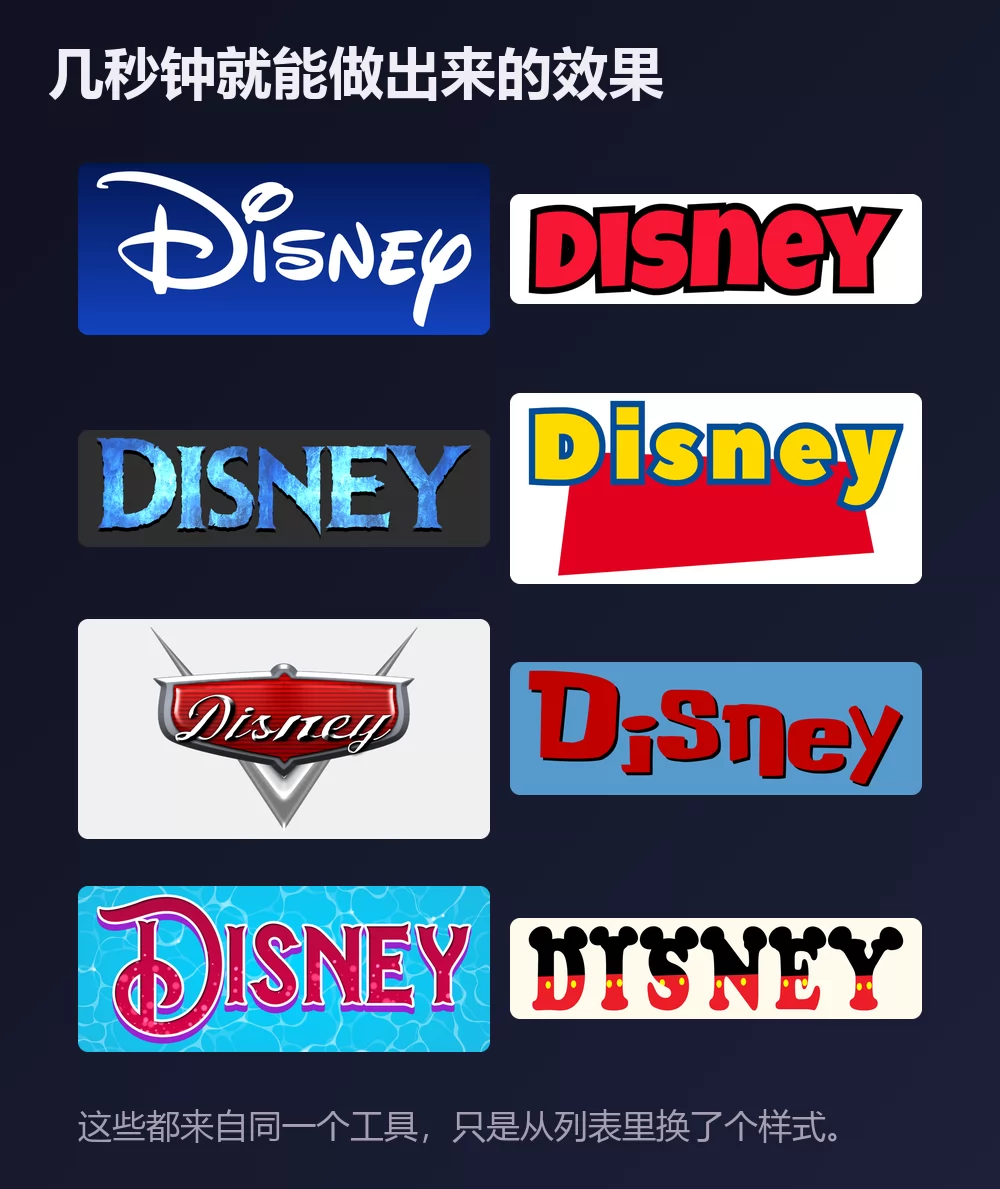
这些都来自同一个迪士尼字体生成器,只是从列表里换了个样式。无需安装,无需账号。
关于迪士尼字体
华特迪士尼公司由华特·迪士尼和罗伊·O·迪士尼兄弟于 1923 年创立,如今已是全球最大的媒体公司之一。米奇是它最知名的角色,也是官方吉祥物。
标志上的字样是华特·迪士尼签名的风格化版本。它从 1956 年起就是公司标志,却从未作为字体发布:没有任何官方文件可供安装。大家转而下载的是 Waltograph,由 Justin Callaghan 按照标志字样绘制。它有两个版本:Waltograph 42,含大小写字母,外加少量连字和替代字形;Waltograph UI,一种单一大小写的版本,为的是在小字号和屏幕上依然清晰。两者都可免费用于个人用途。
怎样做迪士尼文字
第一步:输入名字
打开生成器,把示例文字换成你自己的:孩子的名字、派对的标题、旅行 T 恤上的姓氏。字母会随着输入实时重绘。请保持首字母大写、其余小写:签名风格是手写体,全部大写会丢掉那个高高绕圈的 D,而它正是让人一眼认出迪士尼的关键。
第二步:挑一个样式
经典款是宝蓝色渐变上的白色签名体。在"样式"选项卡里,填充、描边和阴影可以分别调整,所以你可以保留字形,把颜色换到别处:婚礼用深蓝配金色,公主派对用粉色。
第三步:选好尺寸
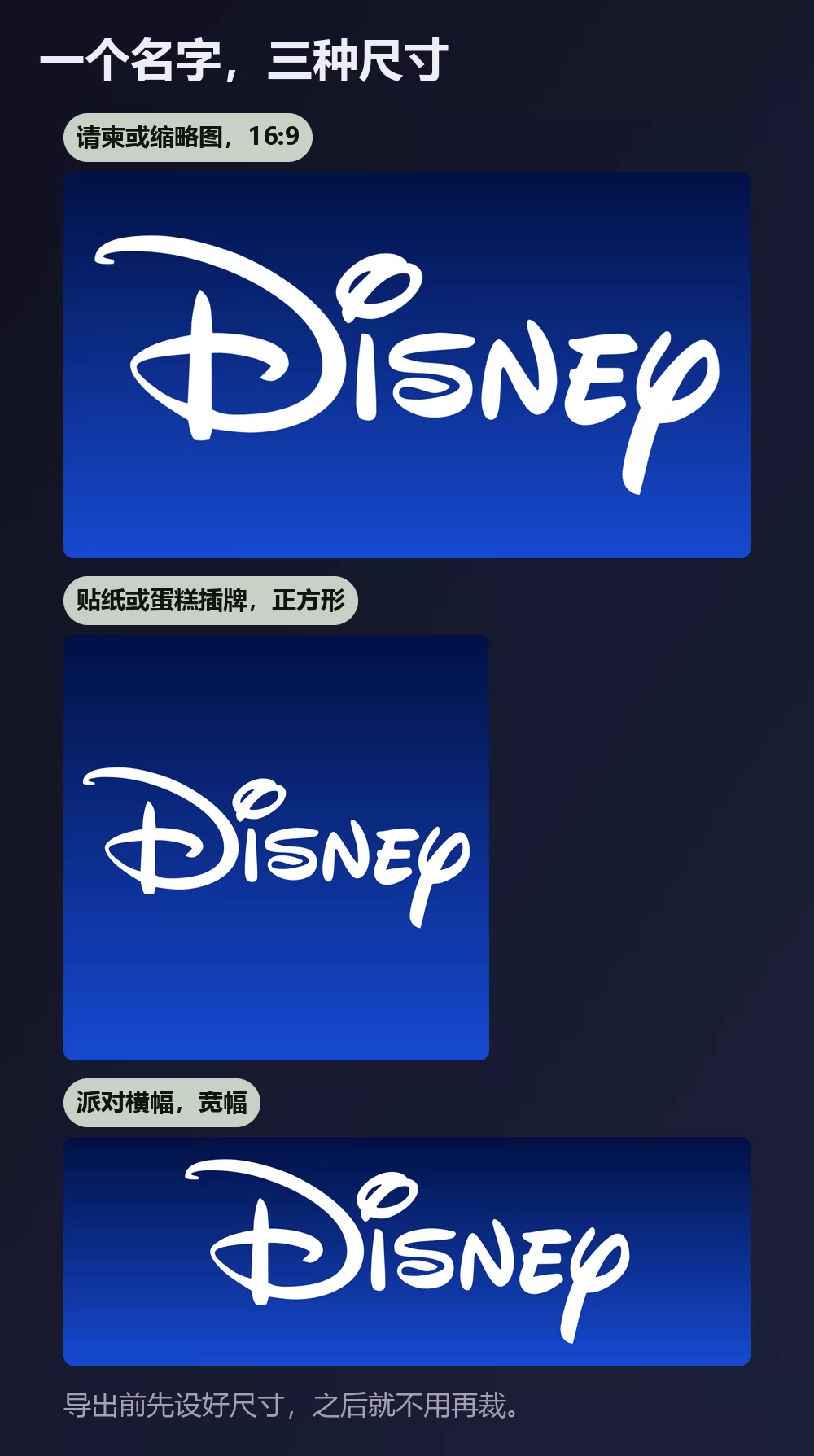
导出前先设好尺寸,之后就不用再裁。请柬或视频缩略图用 16:9,贴纸或蛋糕插牌用正方形,挂在墙上的横幅用宽条。
第四步:下载
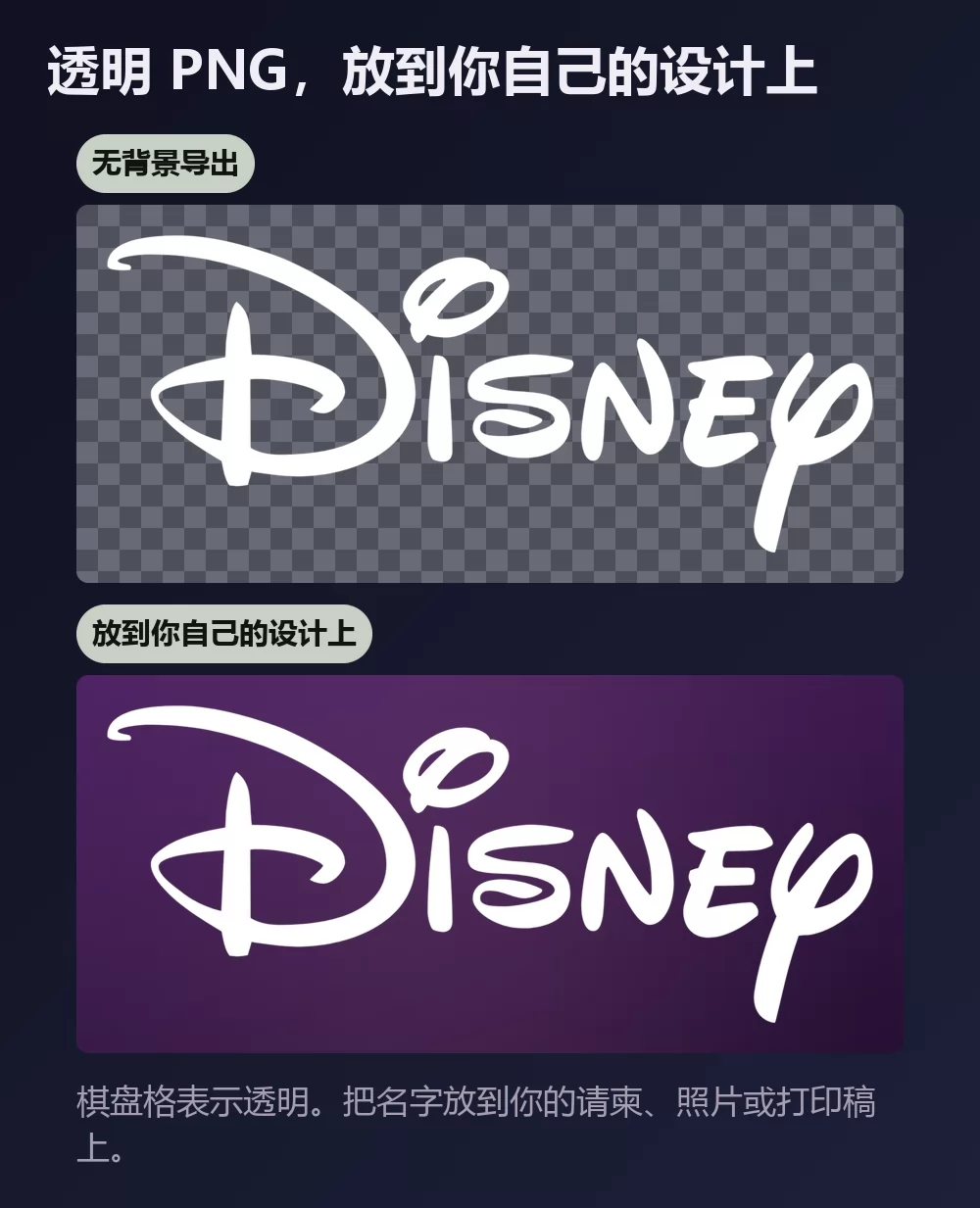
如果打算把名字放到自己的设计上,就在"下载"选项卡里选透明 PNG。这是大多数人错过的选项,而对派对打印品来说恰恰是最要紧的:你自己的背景,名字在上面,周围没有蓝色方框。
名字一长,宽度很快就满了
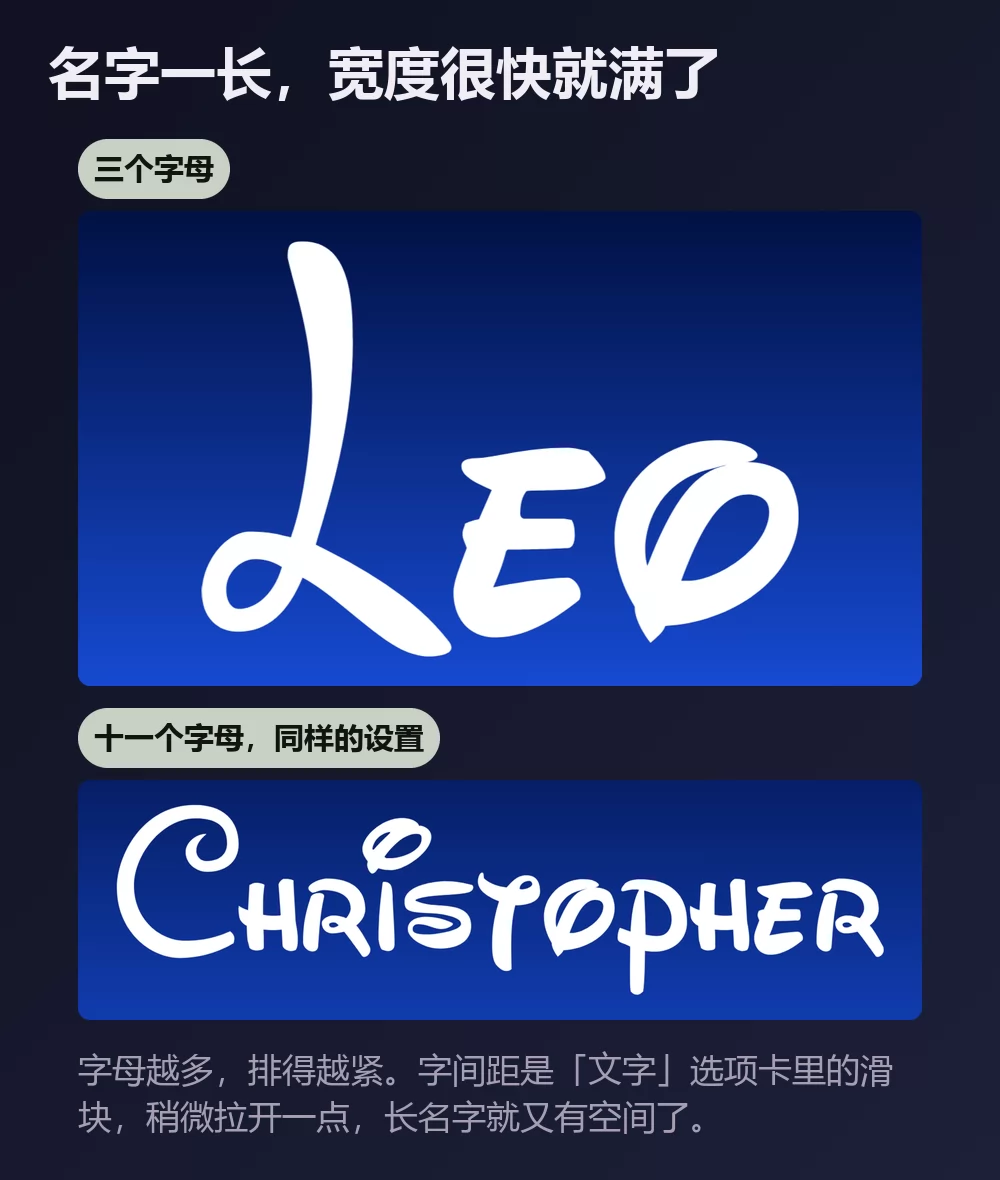
字母越多,排得越紧。字间距是"文字"选项卡里的滑块:稍微拉开一点,长名字就不再显得局促。同一个选项卡里还有缩放、行高、弧度和旋转。
签名风格,还是米奇风格
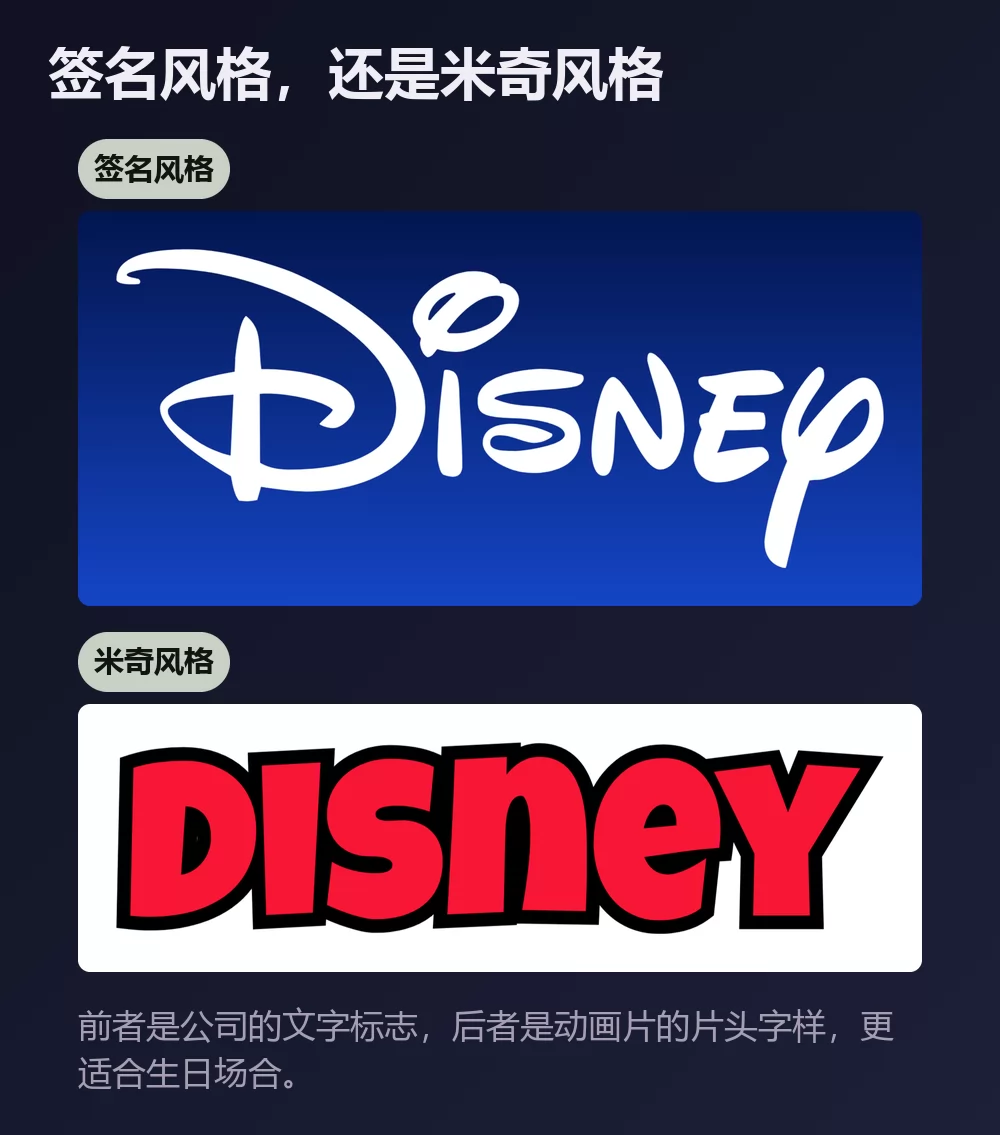
签名风格是公司的文字标志:流畅的手写体,带高高绕圈的 D,蓝底白字。大多数人说"迪士尼字体"时,脑子里想的就是它。
米奇风格是动画片的片头字样:带黑色描边的粗壮红色大写字母,米奇短片里用的那种。它不带任何公司标识,隔着房间也看得清,办周岁生日的话通常比签名体更合适。米奇字体生成器里有现成的预设。
想安装字体的话,选哪一款
标志本身不是字体。它是定制的手绘字样,所以任何叫"迪士尼字体"的文件,都是别人对它的再现。
Waltograph,Justin Callaghan 所作,是大家都在用的那款再现。它在 DaFont 上已有大约二十年,下载量超过一千三百万次。下载包里有两个文件,waltograph42.otf 和 waltographUI.ttf,标注为个人使用免费。个人使用指的是孩子的生日请柬或全家旅行的 T 恤,而不是你拿来卖的产品。
New Waltograph,538Fonts 所作,是 FontSpace 上的一个改良版本,也是那里下载最多的迪士尼风格字体。FontSpace 把它标为 100% 免费,在那个网站上这包括商用。为客户项目采用之前,请先读一读下载包里的 readme。
Mouse Memoirs,Astigmatic 所作,是授权必须干净时的选择。它自 2012 年起就以 Open Font License 收录于 Google Fonts,因此可免费商用。它不是签名的复制品:而是一款高瘦的手绘无衬线体,带着早期动画的气息,在海报或菜单上与签名风格搭配得很好。
按电影和角色分的迪士尼字体
公司标志是一回事。每部电影都有自己的标题字样,搜索"迪士尼字体"得到的大多数结果,其实就是这些字样的清单。同一个生成器几乎为每一部都准备了样式,各有各的页面:
- 米奇字体:带黑色描边的粗壮红色大写字母
- 米妮字体:粉色波点,每个字母上都有蝴蝶结
- 冰雪奇缘字体:边缘结霜的冰蓝色大写字母
- 玩具总动员字体:红色色块上带蓝色描边的黄色字母,我们还有一篇玩具总动员完整指南
- 赛车总动员字体:带红色手写字的镀铬徽标,像是直接从引擎盖上取下来的
- 星际宝贝字体:蓝底上手绘的红色字母
- 小美人鱼字体:水面上华丽的紫色衬线体
- 小熊维尼字体:黄边红字,置身林间
- 狮子王字体、小飞侠字体、怪兽电力公司字体、海洋奇缘字体、魔发奇缘字体、魔法满屋字体、寻梦环游记字体和海底总动员字体
全套都在迪士尼文字特效页面上,还有角色本人的字母表:戴着米奇耳朵和短裤的字母、唐老鸭的水手服、公主们的配色。
怎样在 Canva 里做迪士尼文字
Canva 没有 Waltograph,它的字体库里也没有任何一款像那个签名。把字样做成透明 PNG 再上传:它能直接放进 Canva 设计里,而且在打印尺寸下依然清晰,这对请柬来说很重要。
怎样在 Photoshop 里做迪士尼文字
安装 Waltograph,以首字母大写输入名字,然后用图层样式搭出效果:
- 颜色叠加,纯白。
- 投影,柔和的深蓝色,低不透明度,让手写体从背景上浮起来,又没有生硬的边缘。
- 在下面的图层上加一层渐变,顶部浅宝蓝,底部深海军蓝。
不要描边。签名本来就没有轮廓,加上描边是让它看起来像仿冒品的最快方式。
怎样在 Word 里做迪士尼文字
安装 Waltograph,输入名字,保持首字母大写。Word 可以给字母填色并加一层柔和的阴影,这个样式需要的其实也就这些。渐变的页面背景打印效果很差,所以凡是要分发的东西,在自己的背景上放一张导出的 PNG 会更好看。
在手机上
常见问题
迪士尼标志用的是什么字体? 没有字体。它是华特·迪士尼签名的风格化版本,作为定制字样绘制,从未作为字体发布。Waltograph 是最接近的再现。
有没有可以商用的迪士尼风格字体? Mouse Memoirs,在 Google Fonts 上以 Open Font License 发布。它是神韵上的迪士尼,而不是签名的复制品。
Waltograph 42 和 Waltograph UI 有什么区别? Waltograph 42 有大小写字母,带连字和替代字形。Waltograph UI 是单一大小写,专为小字号和屏幕上的清晰度而绘制。
要用大写输入吗? 不要。签名是手写体,它的神韵来自高高绕圈的 D 和小写字母。全部大写就丢了。
做请柬时怎样得到透明背景? 在"下载"选项卡里选透明 PNG,然后把名字放到你自己的纸张、照片或打印稿上。